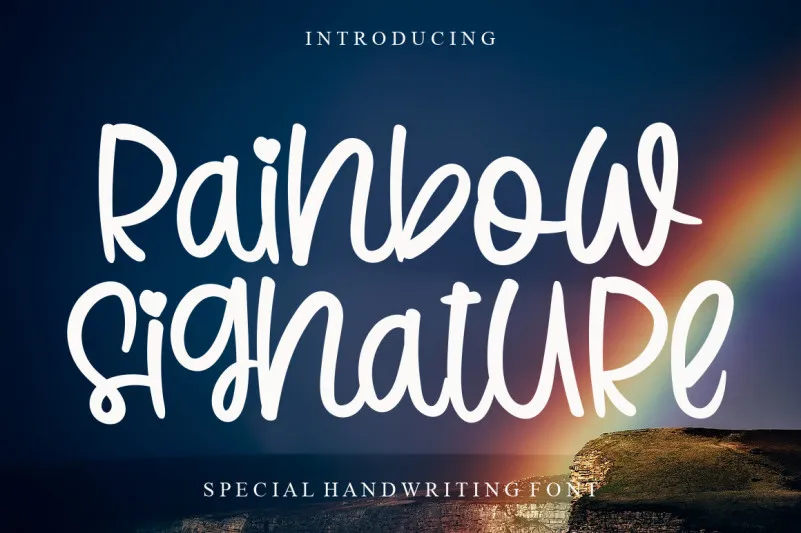
Rainbow Signature Font – Fonte Grátis
Rainbow Signature Font
A Rainbow Signature Font é uma elegante escolha para designers que buscam personalidade e romantismo em seus projetos digitais. Desenvolvida pelo designer LevinCreative, essa fonte escrita à mão apresenta caracteres com curvas perfeitas e traços amigáveis, adequados para um amplo leque de usos criativos. Perfeito para encontros íntimos como festas de casamento e aniversários, além de projetos que valorizam a autenticidade, como cartões de boletim ou logotipos em marcas d’água personalizados. Seja qual seja o projeto, essa fonte trará um toque único e apaixonado à sua criação.